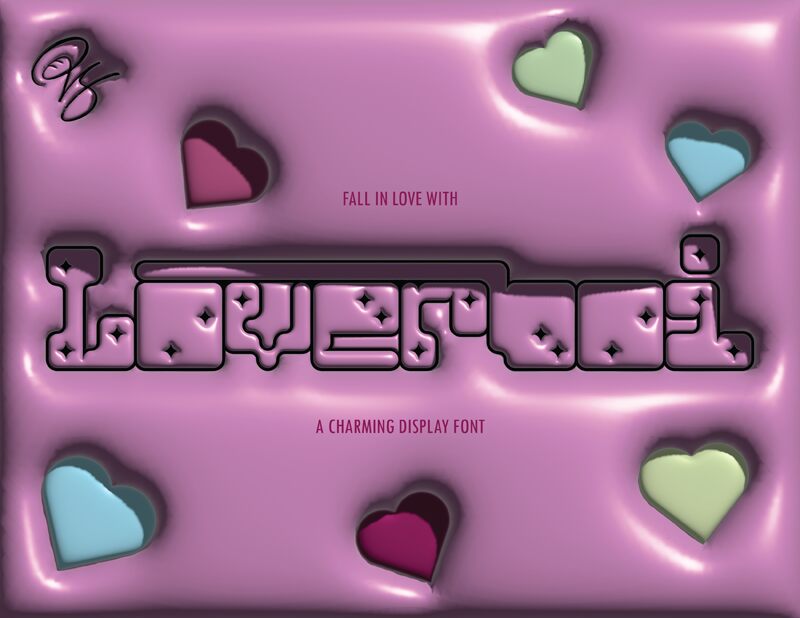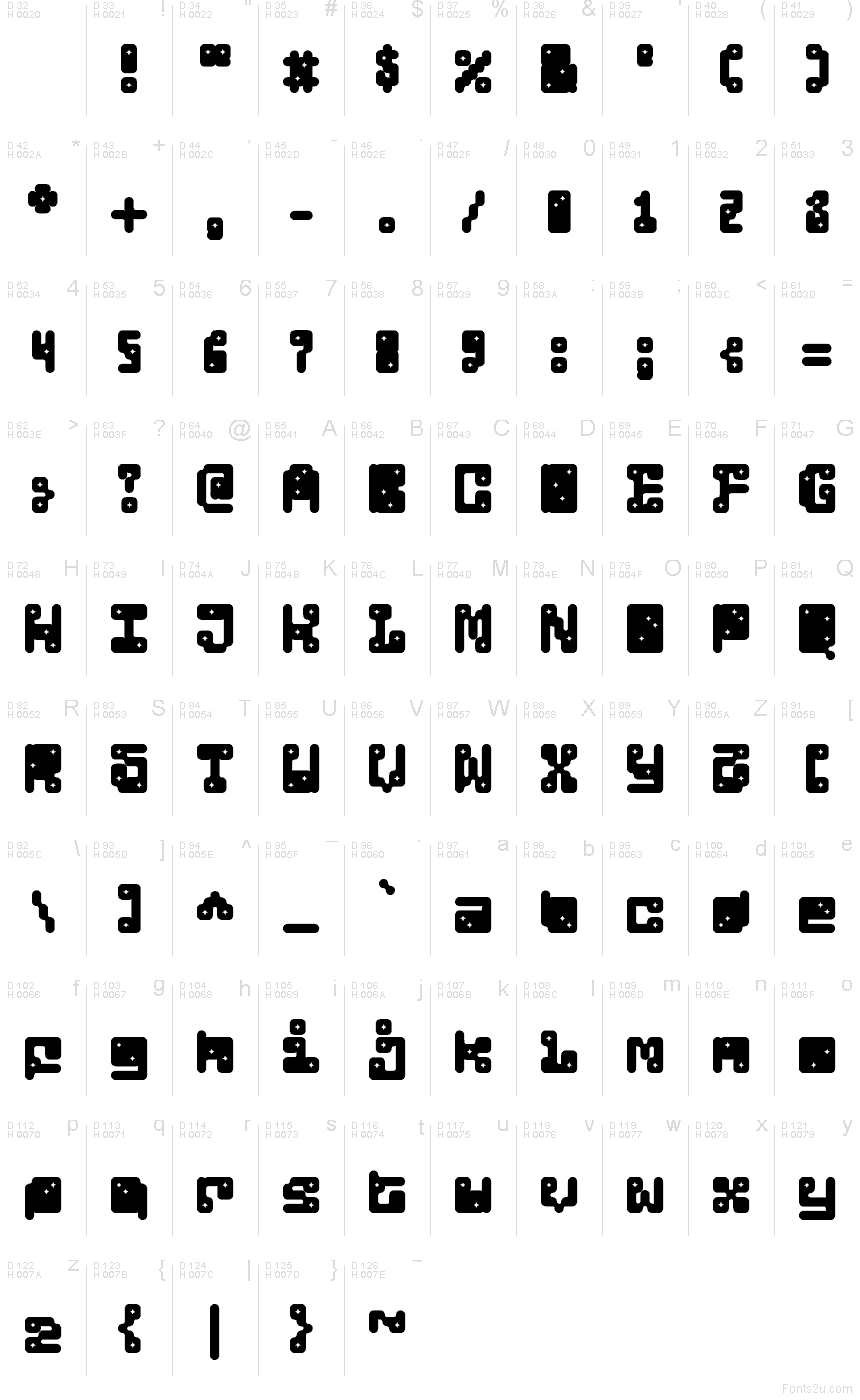
Loverboi Silhouette od Pendesal Studio je bezplatné groovy bezpätkové písmo typu display, tvorené radom zaoblených čiernych modulov. Vďaka baňatým zakončeniam a malým hviezdicovým výrezom sa písmená menia na kompaktnú popovú siluetu. Dizajn pôsobí menej detailmi obrysov a viac svojou celistvou masou, čo každému slovu dodáva mäkký a plagátový vzhľad.
Táto silueta skvele ukotví hudobné letáky, návrhy nálepiek, obaly albumov, pozvánky na párty a veľké nadpisy na sociálnych sieťach, kde musia písmená fungovať rovnako dobre ako grafika samotná. Hviezdicové výrezy a zaoblené rohy z neho robia prirodzenú voľbu pre módny branding alebo hravé obaly, ktoré chcú pôsobiť sladšie a menej agresívne.